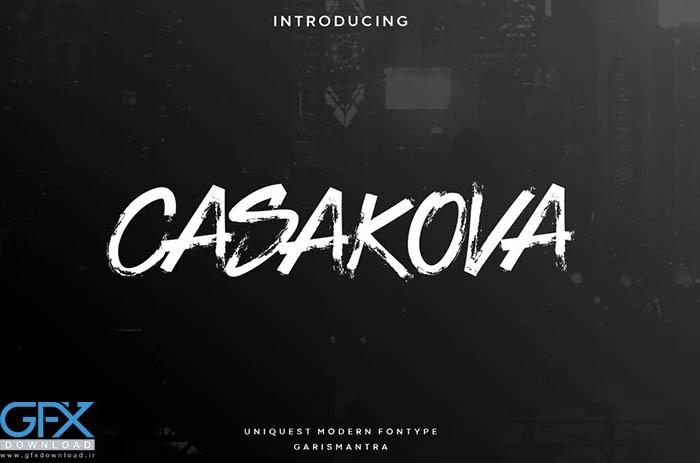
فونت انگلیسی Casakova
Casakova یک فونت با طرح براش ناهموار با حروف بزرگ، سبک دست خط ساده است، اما هنوز هم جذاب به نظر می رسد. دارای یک افکت قلم مو برای پویایی بیشتر است و به هنر خیابانی و فرهنگ پاپ احساس می کند. این فونت بسیار چند منظوره است، برای عناوین، طرح‌های تصویرسازی، برچسب‌گذاری، طرح‌های تی‌شرت یا سایر موضوعات طراحی مناسب خواهد بود. برای دانلود رایگان فونت Casakova از جی اف ایکس دانلود به ادامه مطلب مراجعه کنید.